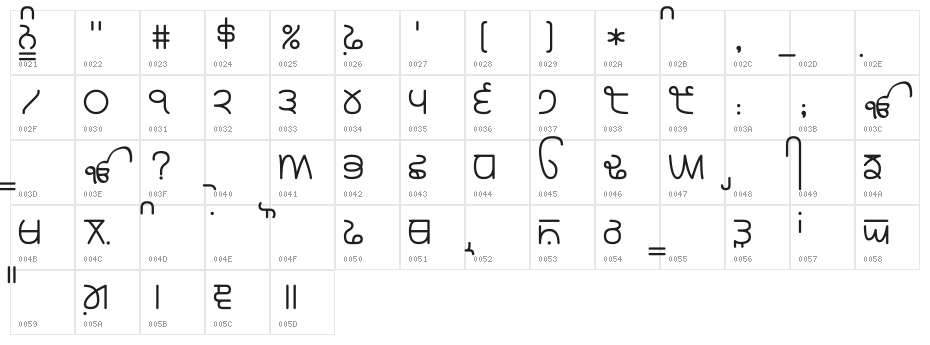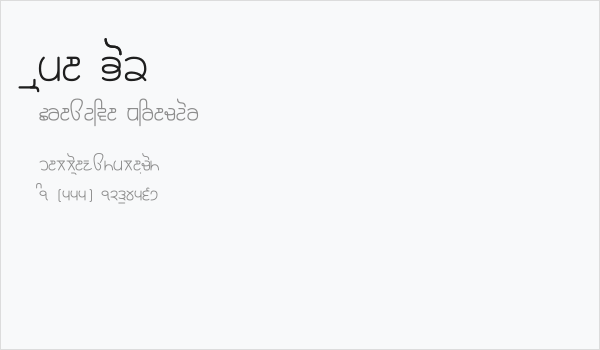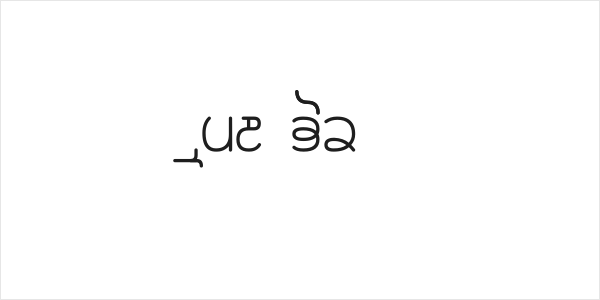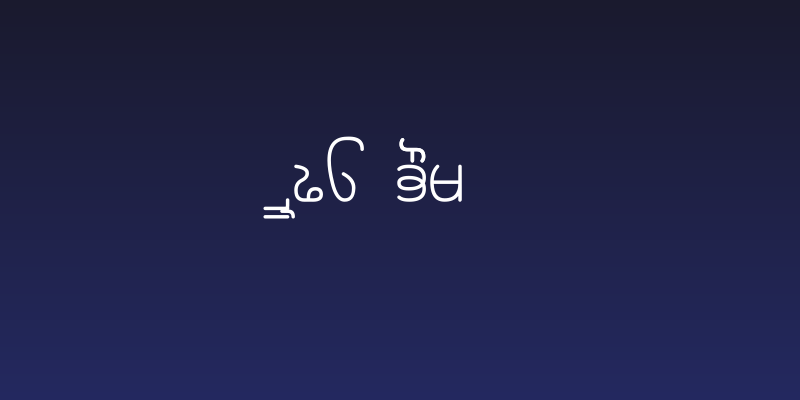
Rupe Book Font
此字体包含 315 个字符。点击任意字符查看详情。
| 整体风格 | Modern, Decorative |
| 使用场景 | Logos, Posters, Artistic projects |
| 推荐项目 | Ideal for creative projects such as album covers, posters, and branding materials that require a modern and artistic touch. |